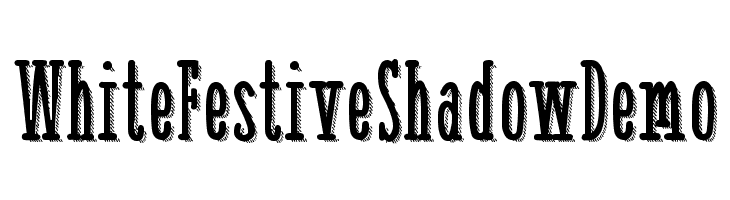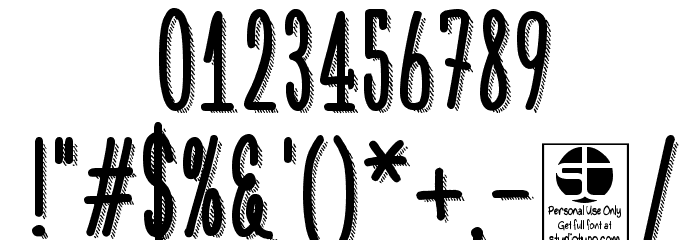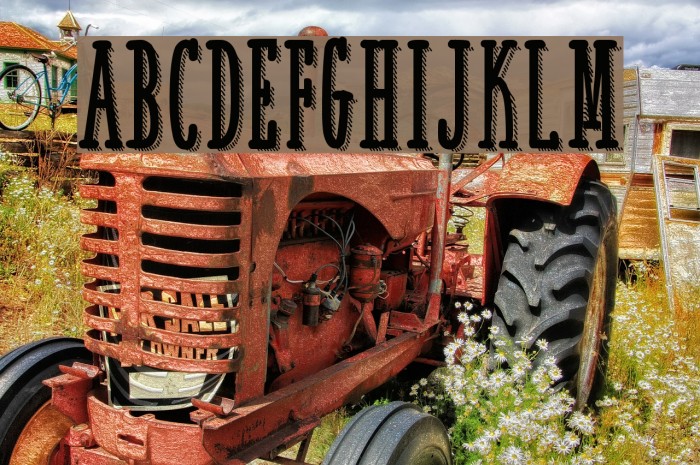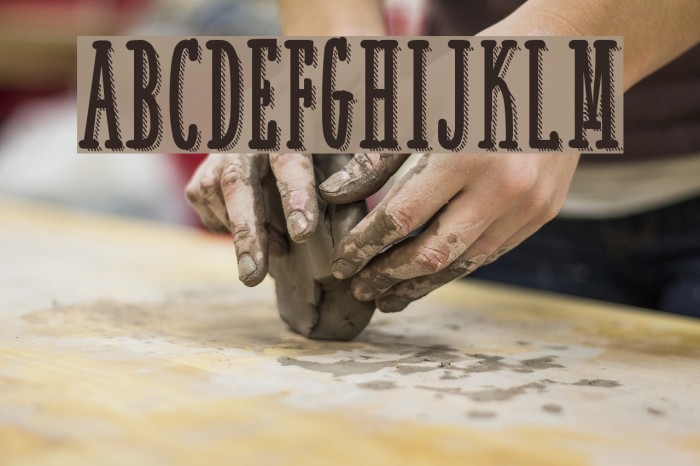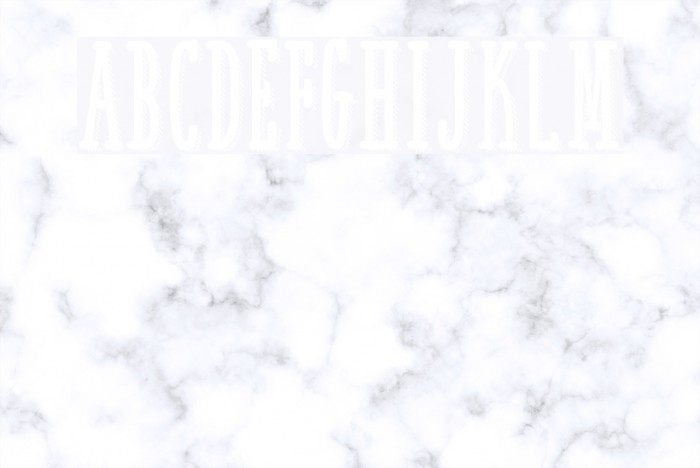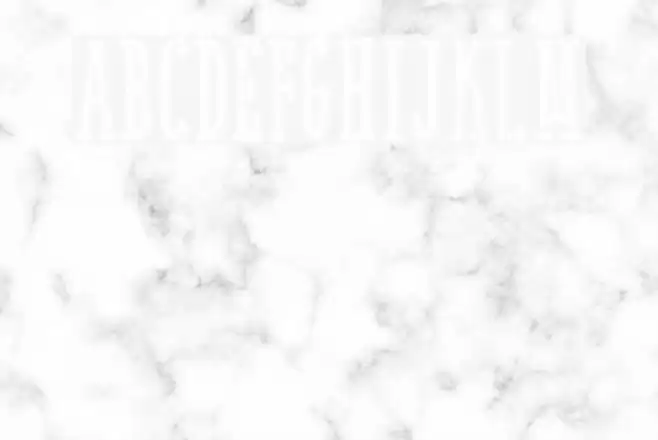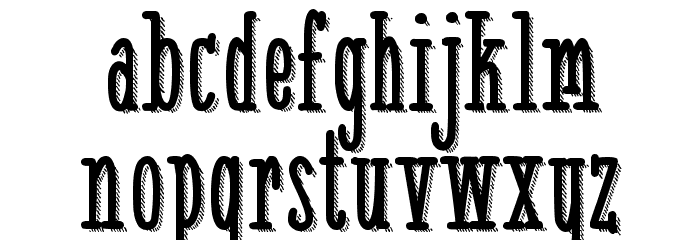
White Festive Shadow Demo Font
| Estilo general | Vintage |
| Proyectos propuestos | Ideal for festive invitations, posters, branding projects, and any design requiring a standout, playful typeface. |